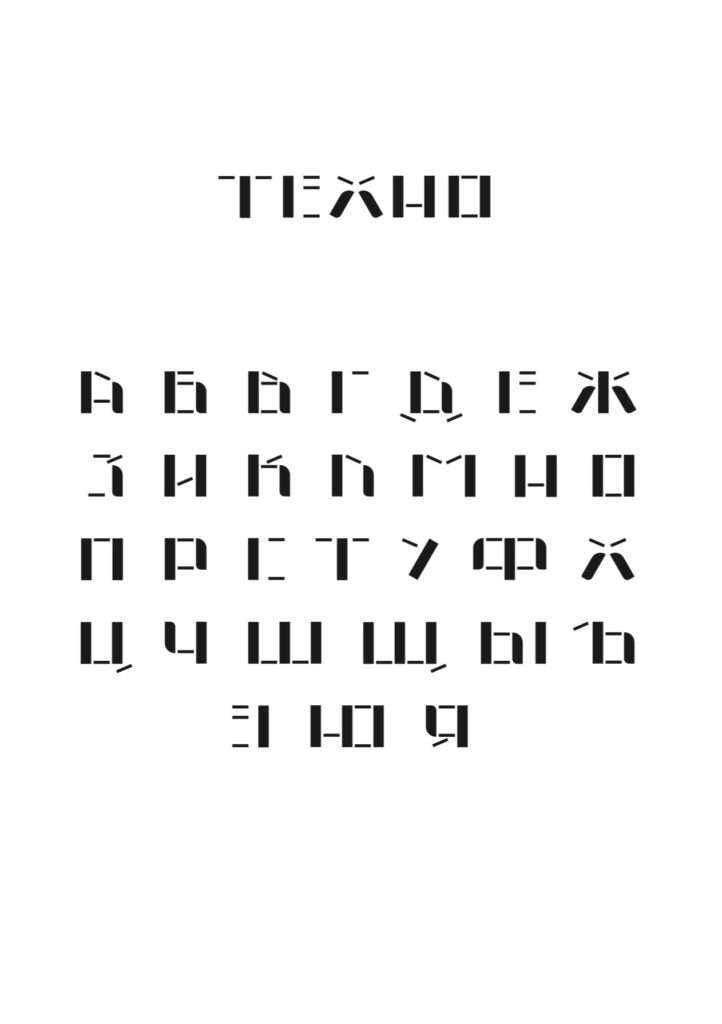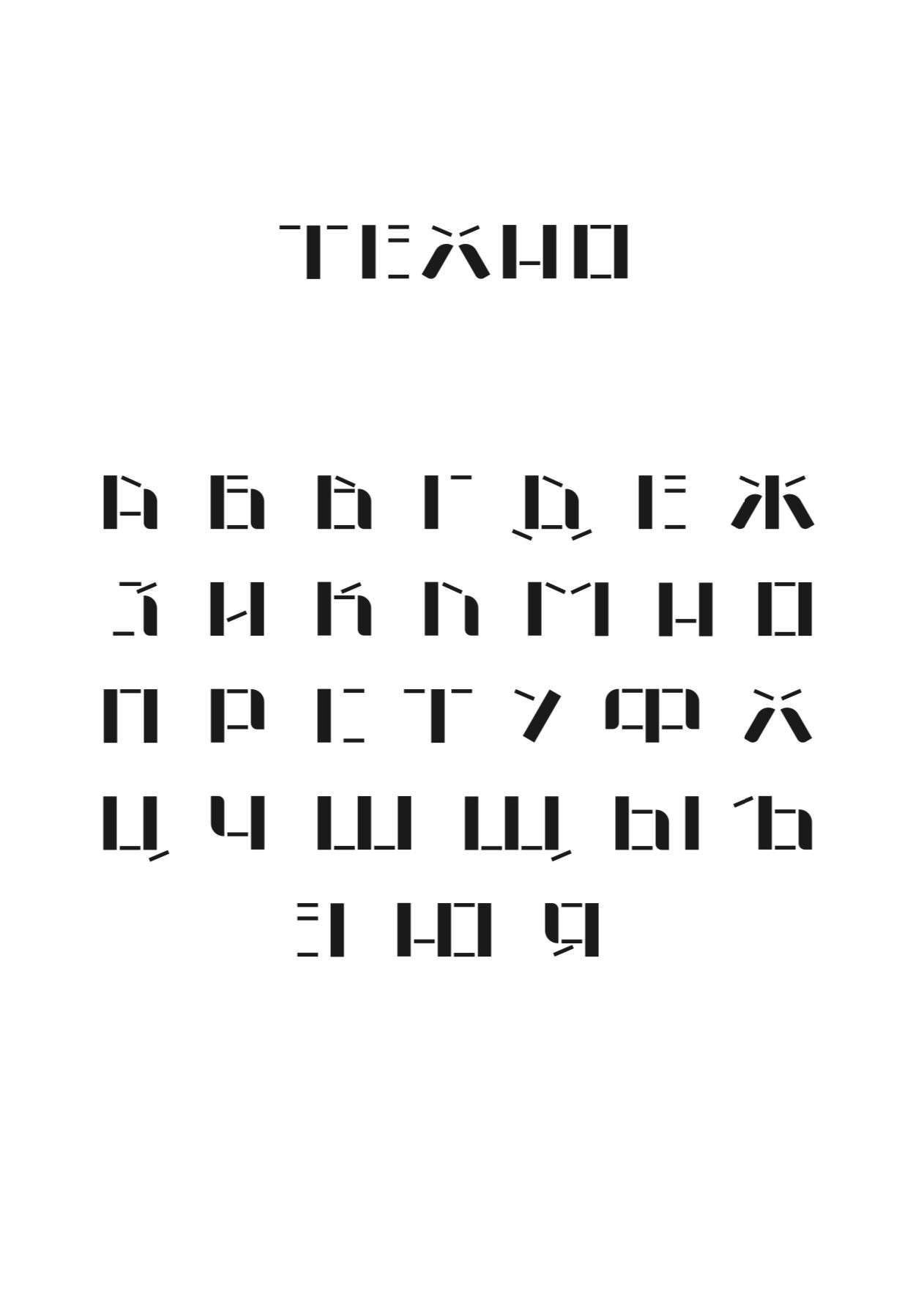
Шрифт Техно
Шрифт Техно — это современный акцидентный шрифт с контрастным начертанием, состоящий из трех модулей. Он может быть использован для создания визуального акцента и привлечения внимания к ключевым элементам дизайна. Он может использоваться в контекстах, где необходимо подчеркнуть динамичность, технологический прогресс и современные тенденции.